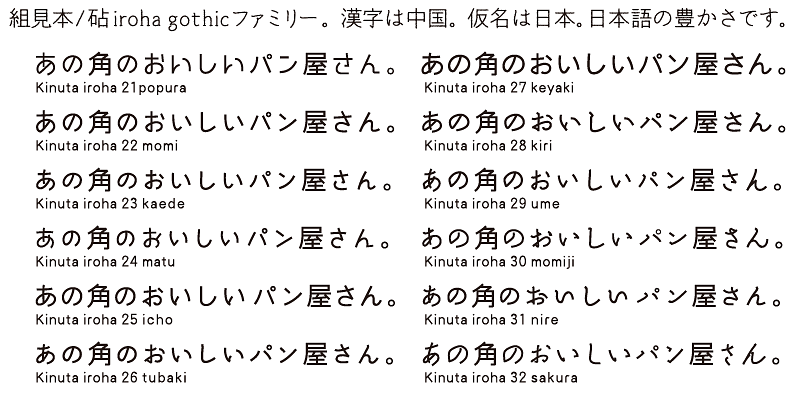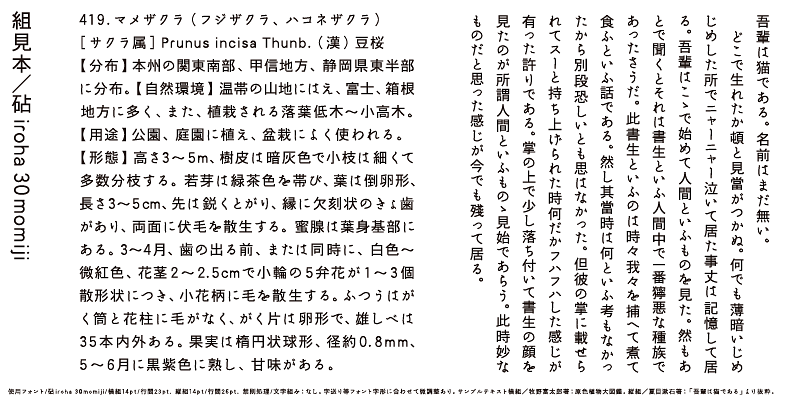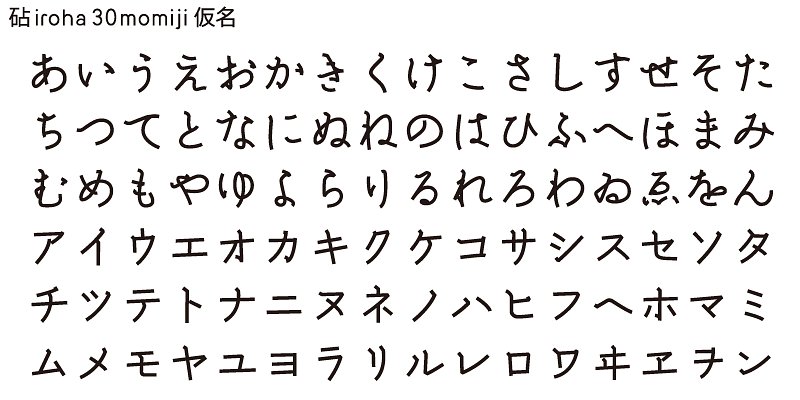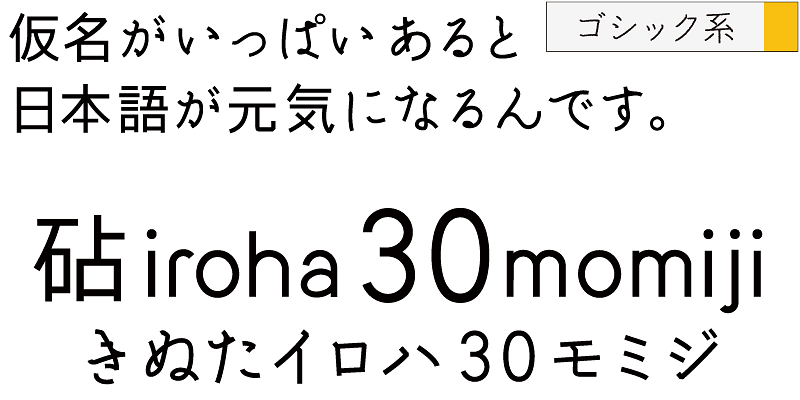
El diseño kana de iroha 30momiji incorpora pinceladas rítmicas. Las curvas de los caracteres kana junto con los trazos lineales de kanji crean una agradable armonía única.
Todas las variantes de Iroha comparten los mismos caracteres ideográficos (kanji). Los caracteres kanji de Iroha están diseñados con trazos lineales y estructuras simples. Hay 12 variantes de kana.
Una característica del japonés es que tiene caracteres silábicos llamados kana. Los caracteres kana se inventaron para representar sonidos en japonés y traducir textos importados de China. Los caracteres kana son necesarios para crear palabras y expresiones japonesas a partir de caracteres ideográficos kanji, que son caracteres chinos. Si bien puede haber ambigüedades, estas palabras y expresiones exhiben la cercanía y amabilidad de las personas que viven en la pequeña y densamente poblada tierra de Japón.
Kinuta Font Factory cree que los caracteres kana son el origen de las palabras escritas en japonés, y que mejorar los caracteres kana hará que el texto japonés sea más atractivo. En promedio, el 60 % del texto japonés se compone de caracteres kana; cambiar la forma de estos caracteres cambia la apariencia visual del texto. Las posibilidades de expresión tipográfica utilizando caracteres kana sencillos, dinámicos y curvilíneos son enormes, y la riqueza del texto japonés depende de ellos en gran medida. Esta es la razón por la que Kinuta Font Factory ofrece muchas variaciones de tipos de letra kana.